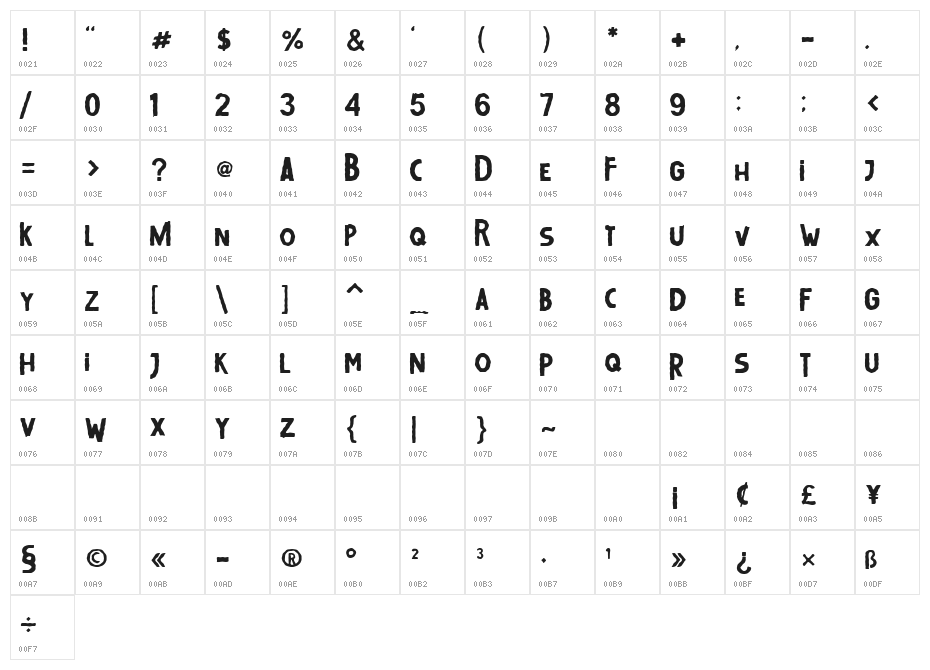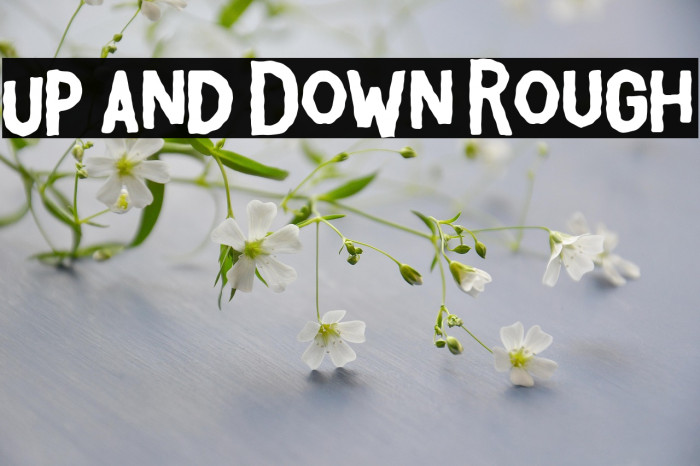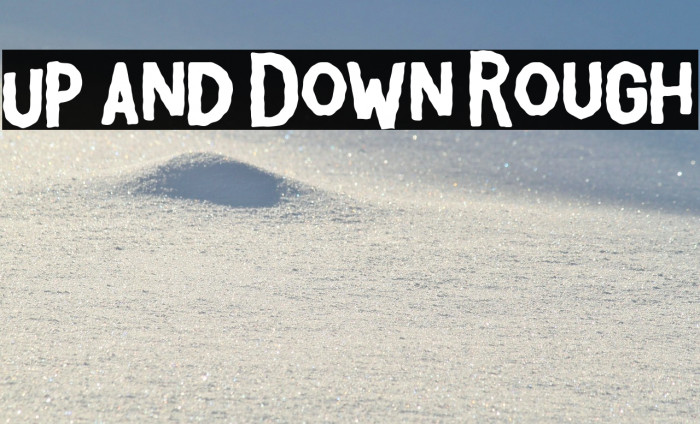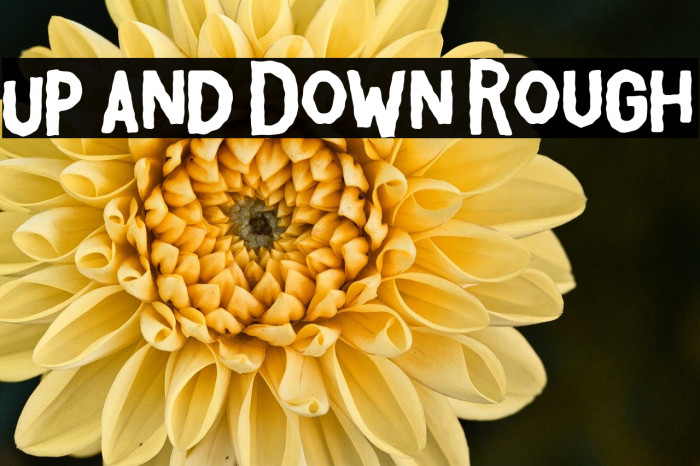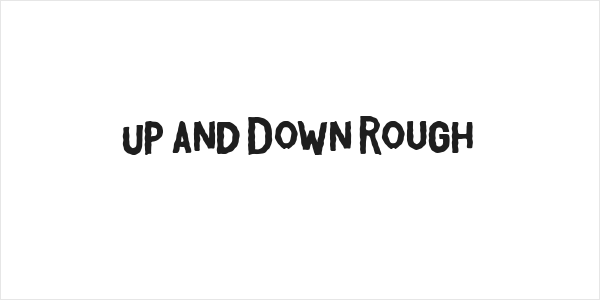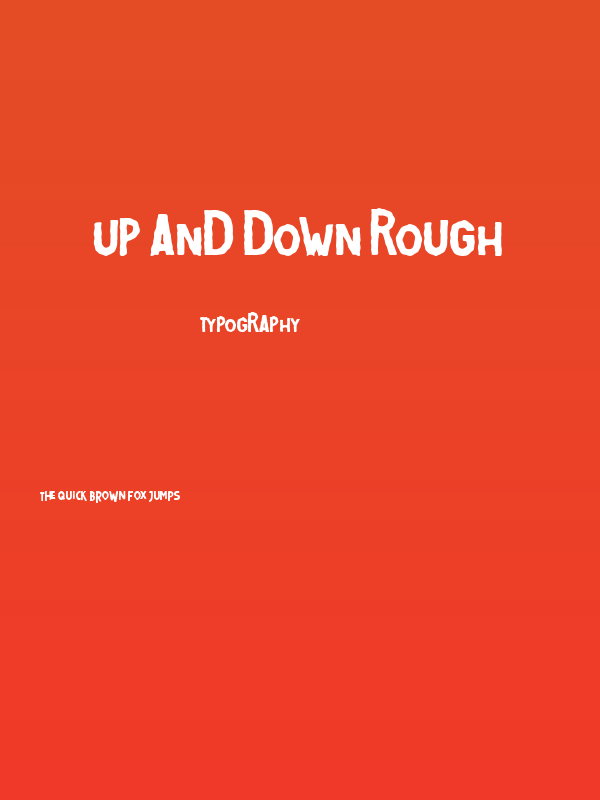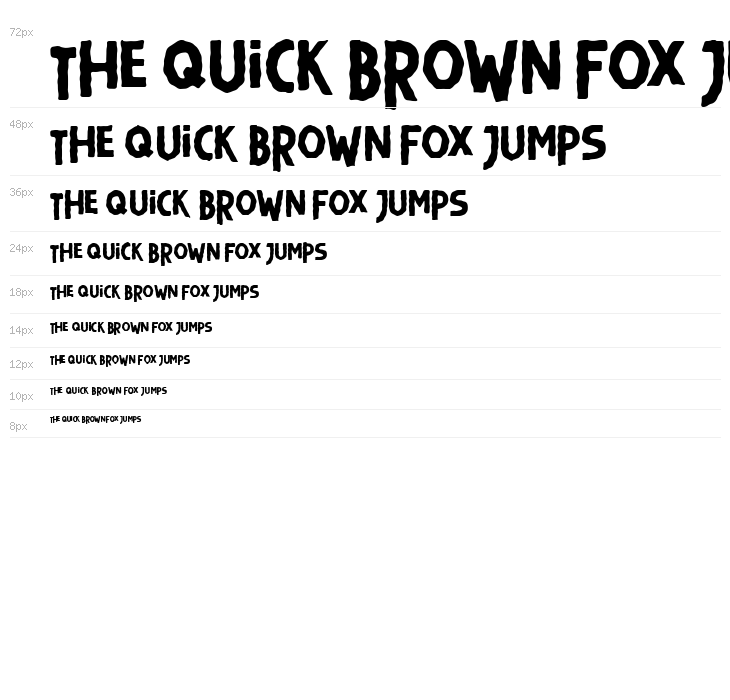
Up and Down Rough Font
| 整体风格 | Playful, Organic |
| 使用场景 | Headlines, Posters, Branding |
| 推荐项目 | Ideal for creative projects such as posters, children's books, and branding that requires a fun and informal touch. |